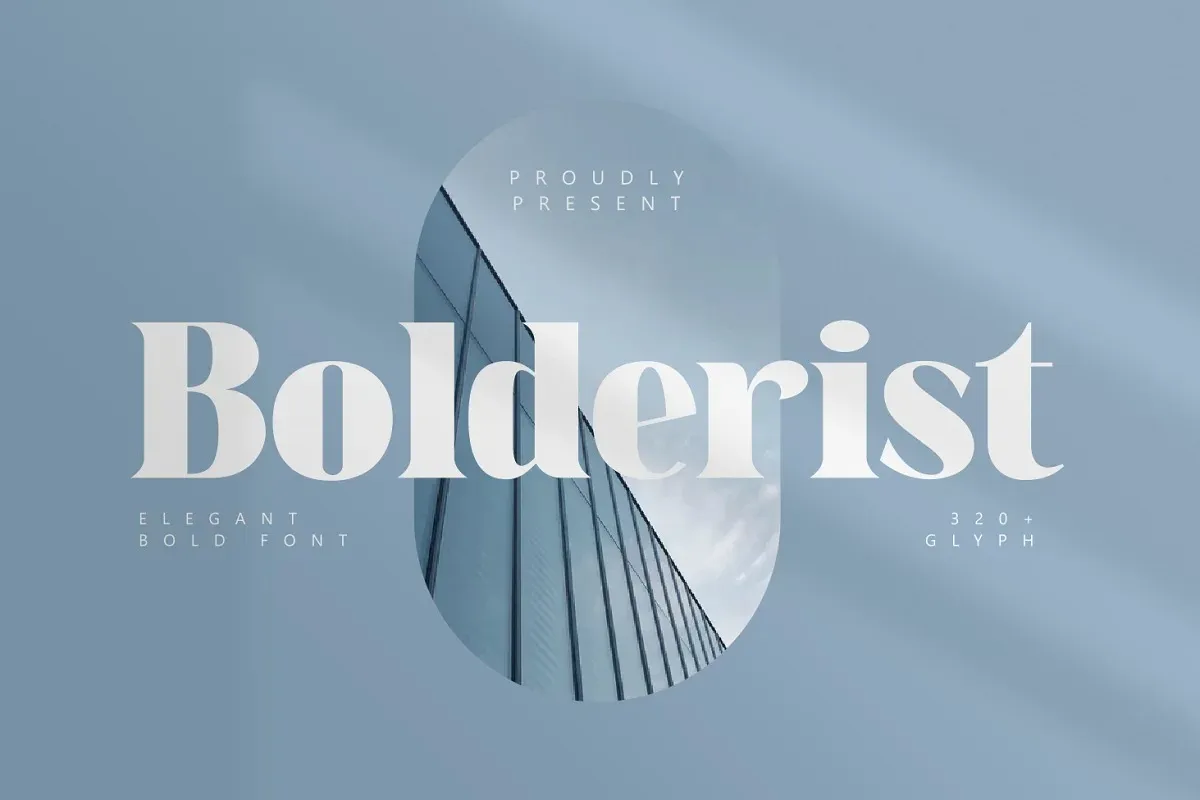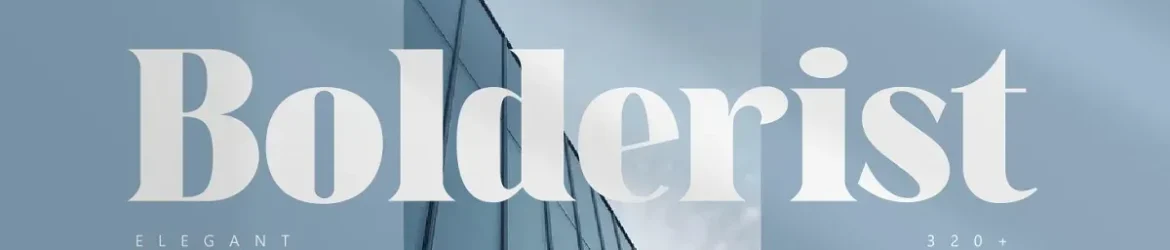
A Bolderist Font é uma elegante fonte serifada moderna criada pela designer zeenesia. Com cada curva integral e pontual no ponto máximo, oferece formas lisas nas duas faces. Bugaki foi projetada para atender a necessidades variadas de design gráfico, sendo particularmente adequada para uso em anúncios, identidade visual, logotipos, embalagens, títulos e headlines, bem como para design editorial. Seu estilo bold e elegante torna-a uma opção ideal para qualquer projeto que exija um estilo chamativo e sofisticado. Não perca a chance de dar vida aos seus projetos com esta fonte única e poderosa.